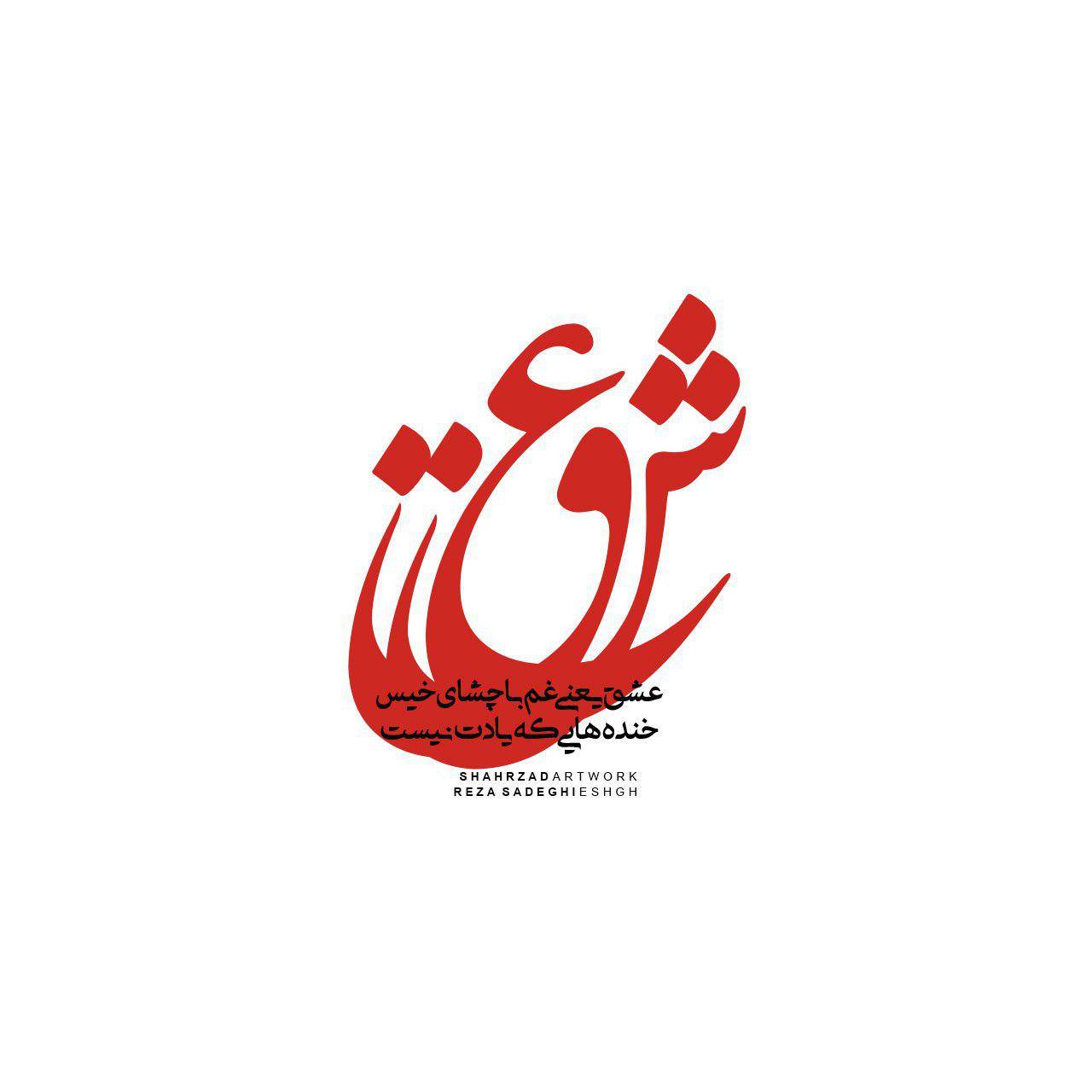
فونت ادوب عربیک شین
آقای صباغی متن زیر را در توضیح انگیزه خود از طراحی این فونت عنوان کردند ادوبی عربیک شین – Adobe arabic shin هنگامی که در بین طراحان بودم میدیدم که بعضی از آنها عاشق «ک» و «ی» های کشیده هستند! و ازین فونت ها استقبال خوبی میکردند. بعضی دیگر هم به دلیل فاصله ی کم حروف در فونت انتظار و تایپوگرافی های کوچک و زیبای آن از این فونت استفاده میکردند. زیاد هم استفاده میکردند! به طوری که یک قدم در خیابان بزنید هر یک فونت تیتری که میبینید یک فونت انتظار هم یه جا میبینید!! حالا که دیدم فونت ادوبی عربیک هم معروف است گفتم بیایم آنرا دستکاری کنم!  خوشبختانه قانون کپی رایت هم در ایران نیست که ادوبی فردا یقه ام را بگیرد و خلاصه من «از هفت دولت آزادم» با قاطعیت می توان فونت ادوبی عربیک Adobe Arabic Font را یکی از بهترین فونت‌های چند سال اخیر دانست. به خاطر ویژگی‌های متعدد و سطح بالا استاندارد این فونت. استقبال زیاد گرافیست ها و طراحان از این فونت زیبا شاهد ما بر این مدعاست. اخیرا دوست عزیزمان جناب آقای شاهین صباغی ادیت جدیدی از این فونت را در اختیار ما قرار دادند تا آن را منتشر کنیم. این فونت زیبا در دو نسخه Adobe arabic shin و Adobe shin stouts منتشر شده است.